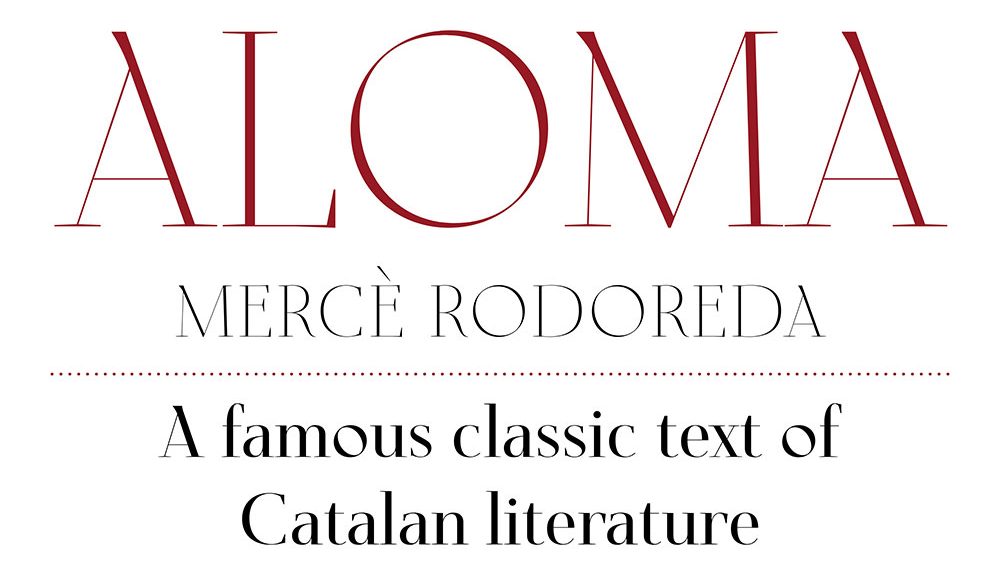
Aloma, nueva tipografía de Typerepublic
Andreu Balius ha diseñado esta familia tipográfica para titulares de cinco pesos y alto contraste. Aloma está inspirada por el Decó y hereda su nombre de un clásico de la literatura catalana.
El proyecto llegó a la oficina de Typerepublic en 2017: una tienda de ropa femenina quería una tipografía propia. Poniéndose manos a la obra, las primeras referencias que Balius consultó fueron revistas y catálogos de moda de los años 50. Tras unos primeros bocetos de una romana moderna de alto contraste, siguió «rebobinando» en su archivo de referencias hasta llegar a los carteles Decó de los años 30. Así, las proporciones empezaron a mutar, el eje de contraste a orbitar y elementos más sugerentes a aparecer.
Lamentablemente, el proyecto acabó cancelado. Sin embargo, en 2019 fue desempolvado como tipografía de catálogo y, durante esta pandemia, rematado. De esta forma, Typerepublic presenta ahora al mundo una Aloma despojada de prejuicios.
Una tipografía segura de sí misma, que luce a tamaños grandes rememorando la ostentosidad tipográfica de la primera mitad del siglo XX.
Sus proporciones —sobre todo de caja alta— y algunas construcciones son evindetemente referencia a otra época, pero maridan muy bien con elementos tan populares en la tipografía contemporánea display como son esas serifas casi filiformes, el contraste extremo o el marcadísimo eje oblicuo de las oes.
En cuanto al nombre, está vinculado al espíritu Noucentista (versión catalana del novecentismo español) y a la escritora Mercè Rodoreda (una de las escritoras en lengua catalana más influyentes de su época) con sus «personajes atados a su tiempo que luchan por sobrevivir y liberarse de una condición impuesta por los convencionalismos de la época» tal y como nos cuenta Balius. Aloma, novela publicada en 1936, nos habla de —sigue Balius—: «una mujer en apariencia sumisa y débil, que se deja llevar por las circunstancias sin aparente oposición. Pero luchará y se enfrentará a sí misma y a los demás escogiendo su propio futuro, incierto sí, pero es el suyo, en definitiva.»